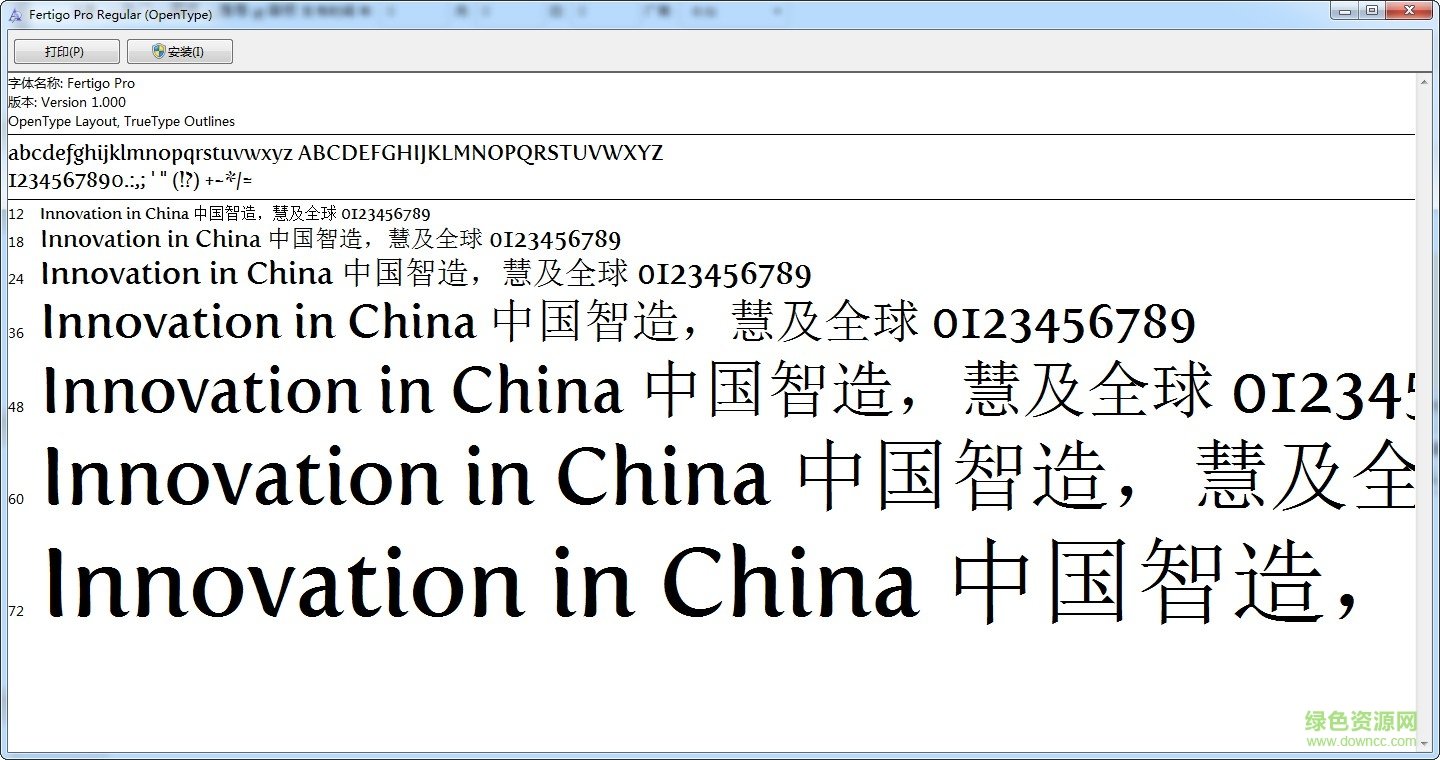
fertigo字體是一款經(jīng)典的襯線字體,該字體線條均勻、筆形柔和、婉轉優(yōu)美,可以用于影視字幕、雜志排版、期刊書籍等領域,歡迎有需要者免費下載!
襯線字體的可讀性非常好,所以它應用的最多的地方也正是出版物或者印刷品的正文內(nèi)容等以大段文字作為表現(xiàn)形式的作品上。